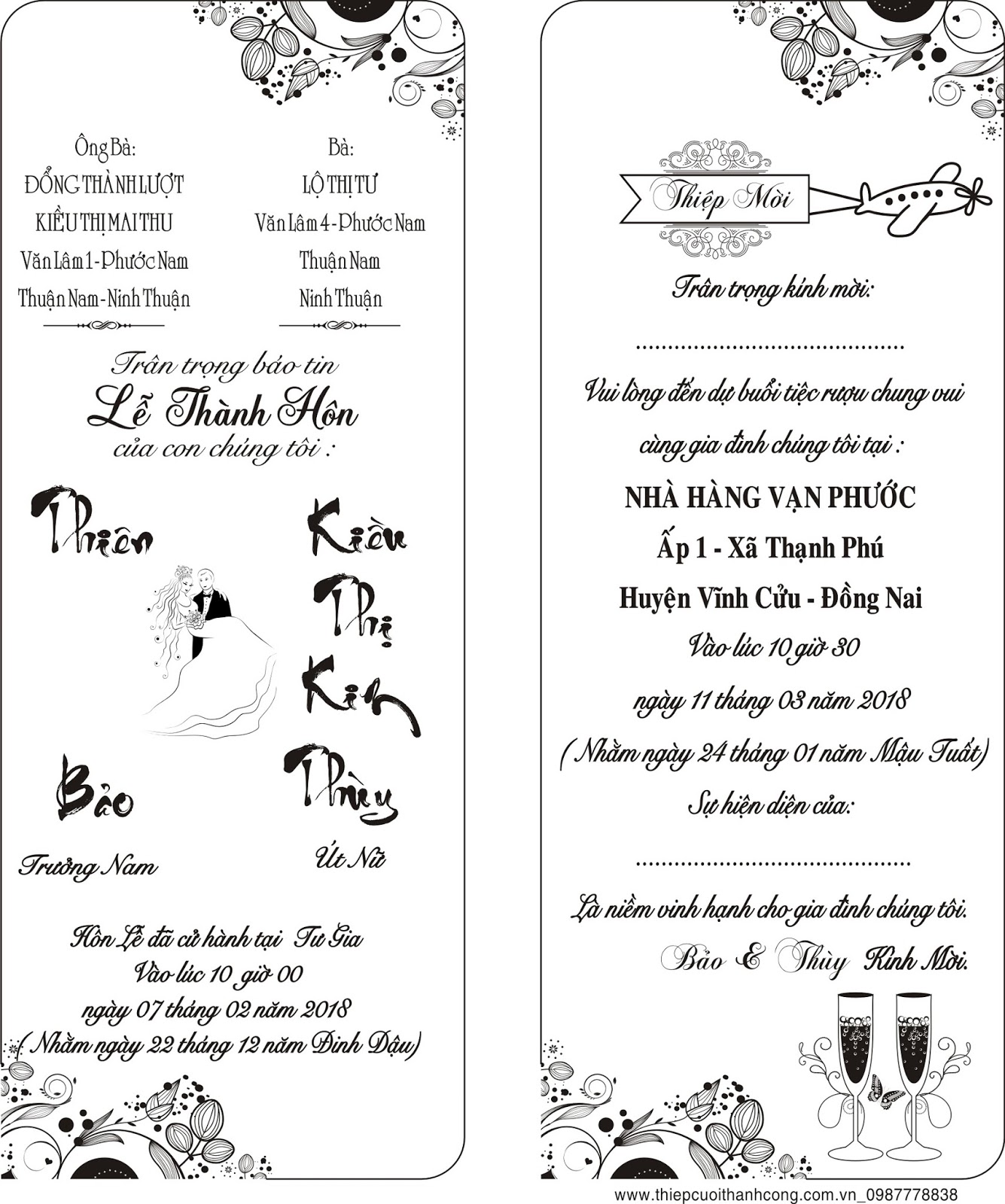
Chia sẻ fonts thư pháp mới nhất 2018. Thư Pháp công thủy
Tex Thử Fonts in thiệp ngay cho khách hàng
Fonts Mới làm in cho khách luôn anh em cho chút ý kiến về viền thiệp & Fonts chữ nào
Em không thích thư pháp Việt viết bằng font máy tính cho lắm, cá nhân em thích những tác phẩm thư pháp viết tay hơn. Vì nó có cái thần, ý, trí, khí trong đó